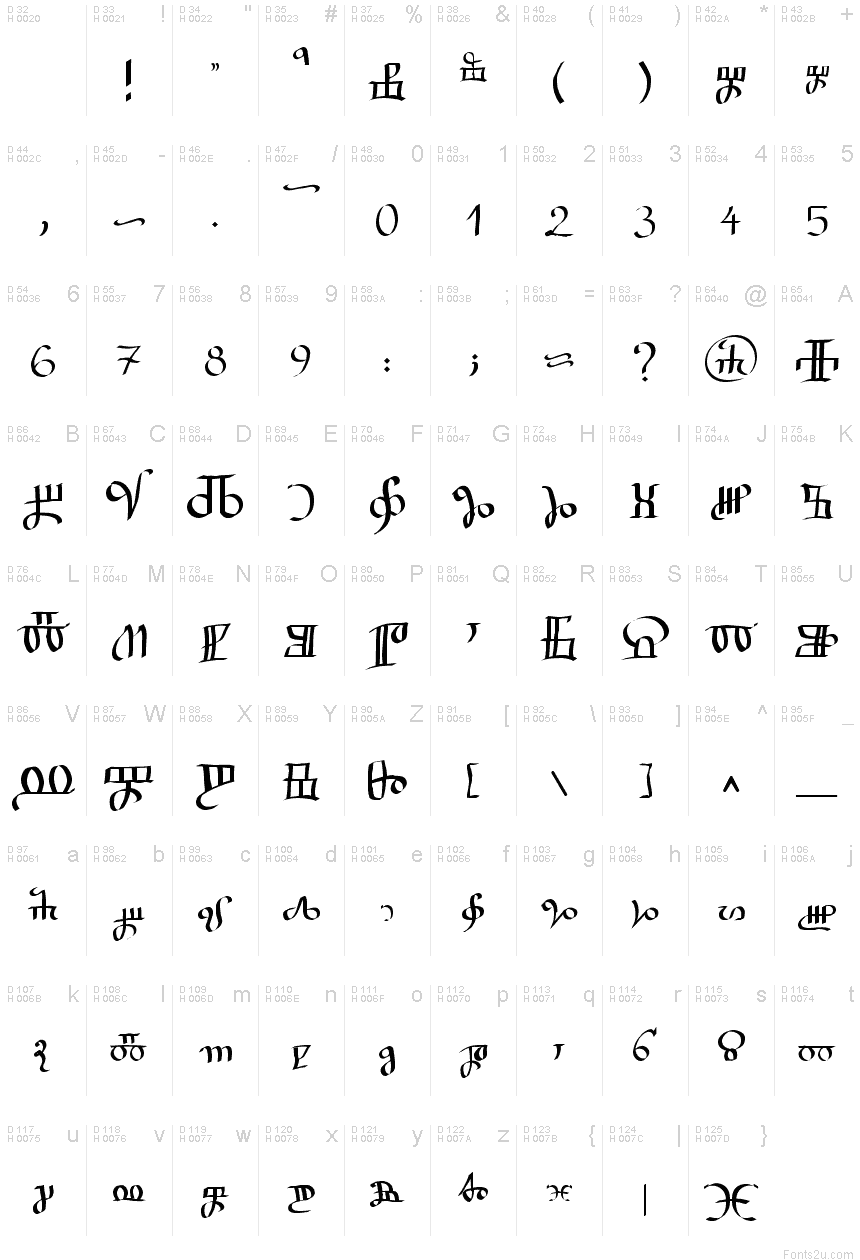
Krcka Notarska Skola 2 è il font medievale slavo gratuito di Eugen Divjak, modellato sulle curve affilate e i tratti ad uncino dell'antica calligrafia. Le lettere hanno un aspetto cerimoniale e leggermente inquieto, mescolando forme ampie e squadrate con punte affusolate e curve arricciate che conferiscono al font un ritmo da scriba davvero distintivo.
È adatto a poster culturali, copertine di libri, grafiche museali, titoli e introduzioni di capitoli in cui il tono storico conta più della neutralità. Trattandosi di un font gratuito, è ideale anche per identità di eventi, artwork di musica folk, o scritte brevi e iniziali in stile monogramma, poiché le lettere possiedono abbastanza carattere d'epoca da funzionare anche con pochi glifi.